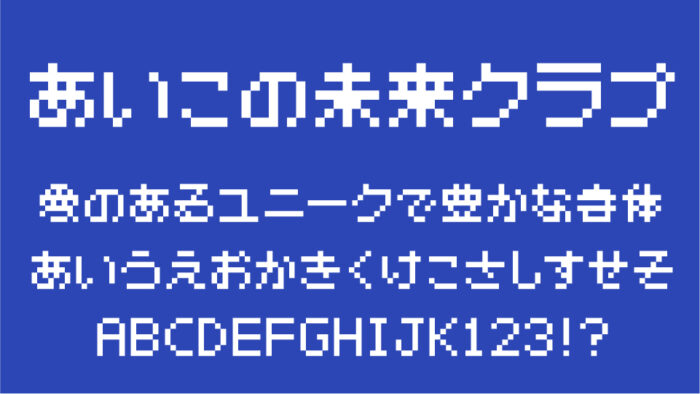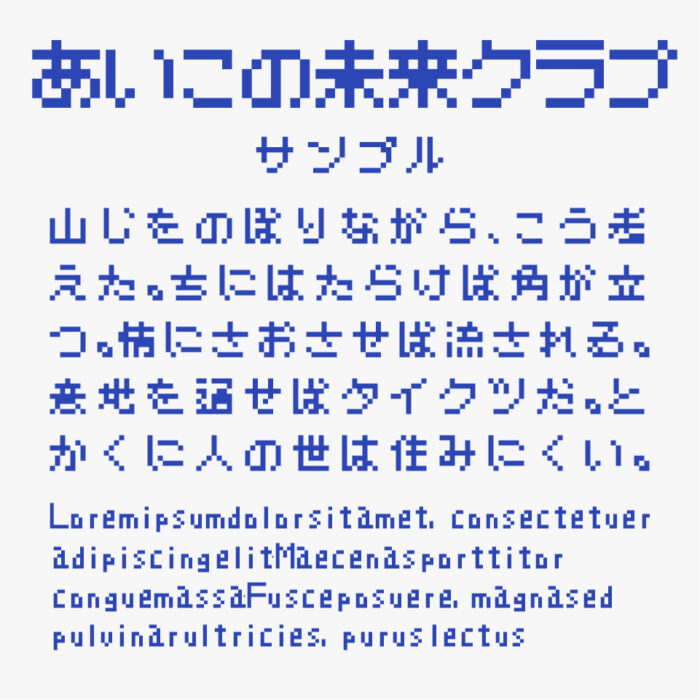
あいこの未来クラブ
あいこの未来クラブフォントは、7×7マスのドットで作られた少し丸みを帯びたフォルムが可愛らしいユニークなビットマップ風フォントです。
カクカクした線で構成されながらも、どこか可愛らしく柔らかい印象を与えるデザインで、ひらがなやカタカナがとくに親しみやすく見えます。
ゲーム系ジャンルはもちろん、イベントロゴ、VTuber・配信者の画面装飾、ピクセルアート風デザインなどにもぴったりなフォントです。
収録文字は、漢字(小学二年生までに習う漢字+α)・ひらがな・カタカナ・アルファベット・数字・記号が収録されています。